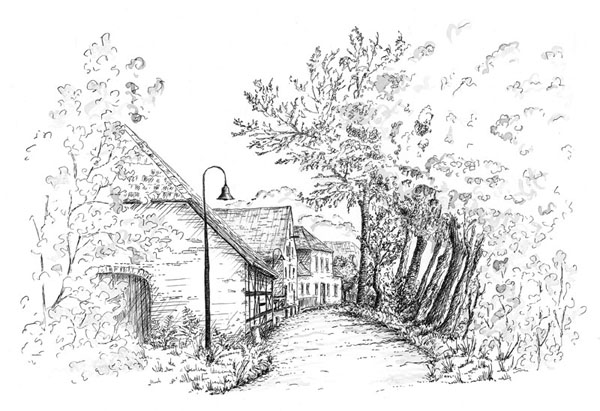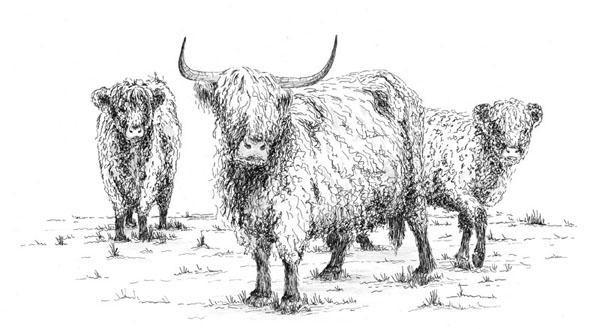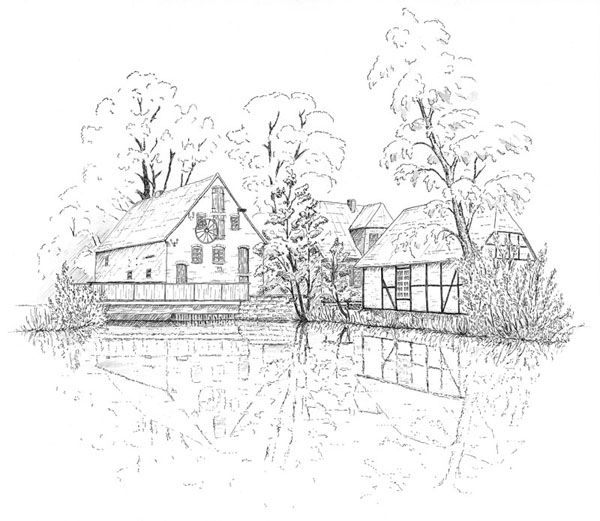
Kalendarium-Gestaltung
für ein anstehendes Kalenderprojekt bin ich auf der Suche nach Inspiration für die Gestaltung des Kalendariums. Erstmal ein paar Hinweise bzgl. des Kalenders vorweg: Es handelt sich um s/w Federzeichnungen von Gebäuden und Landschaften aus der umliegenden Gemeinde. Es soll jeweils eine Zeichnung pro Kalenderblatt gedruckt werden, das Format ist hierbei DIN-A3 quer und es wird ein Wandkalender mit einer Wire-o-Bindung. Unter dem Motiv soll natürlich ein Kalendarium abgedruckt werden und genau hierfür bräuchte ich mal eure Ideen und euer Wissen: Es soll einfarbig sein, evtl. mit Rasterung der Sonn- und Feiertage und praktisch bzw. gut lesbar sein. Die Zielgruppe des Kalenders wird vermutlich 50+ sein.
Für Ideen bzlg. der Gestaltung und der Schriftwahl wäre ich äußerst dankbar! :-)
spontan würde ich da an eine ganz pure, reduzierte Gestaltung denken: Das Kalendarium nur durch feine schwarze Linien gegliedert und eine ausdrucksstarke Schrift mit schönen Zahlen verwendet (sehr schön wären Mediävalziffern), das Ganze sehr klassisch gesetzt. Als Schrift könnte ich mir sowohl eine Serifenlose als auch eine Schrift mit Serifen vorstellen. Wichtig wäre dabei, dass die Schrift mit den Zeichnungen harmoniert und diese betont, statt ihnen die Schau zu stehlen. Könntest Du hier vielleicht mal eine der Zeichnungen einstellen? Dann könnten wir Dir Vorschläge zur Schriftenwahl machen. :-)
So, anbei sind nun drei Beispielmotive für den Kalender. Wie du schon sagtest, sollte das Kalendarium nicht von den Motiven ablenken! Ich bin gespannt auf eure Ideen :-)
Danke fürs Zeigen, die Zeichnungen kann ich mir gut als Kalender vorstellen. Welche Schriften hast Du denn bisher für die Gestaltung des Kalenders schon in Erwägung gezogen?
Ich bin noch in der frühen Anfangsphase was die Schriftwahl betrifft. Ich würde gerne zwei, drei Versionen mit unterschiedlichen Kalendarien erstellen und diese dann andrucken lassen, um damit eine praxisnahe Beurteilung an der Wand zu treffen.
Momentan spiele ich im Kalendarium mit der Helvetica Neue neue herum... gerne würde ich hierbei auf klassische Schriften zurückgreifen, die Zeitlos aber gut lesbar sind.
Da passt doch eine Antiqua.
Zu deinen Zeichnungen kann ich mir die schöne und kostenlose Vollkorn gut vorstellen.
Die würde diese ländlich-heimische Anmutung unterstützen.
Nur so, die Helvetica wäre mir zu "geht irgendwie eh mit allem".
Kann das sein, dass die Unger Fraktur kein ſ beinhaltet?
Mir wäre eine gebrochene Schrift zu dominant zu diesen fein gezeichneten Motiven. Ich würde eher die Eleganz und Zartheit der Motive in einer zurückhaltenden Typografie begleiten.
Aber sagt mal, wo ist denn eigentlich unser Threaderöffner abgeblieben? Ich hatte gehofft, dass wir schöne Kalenderentwürfe zu sehen bekommen. :-)
Mir wäre eine gebrochene Schrift zu dominant zu diesen fein gezeichneten Motiven.
Inwiefern zu dominant? Ich finde, eine feine, elegante gebrochene Schrift würde den Duktus der Zeichungen aufgreifen. Natürlich darf sie nicht allzu schwarz sein, das würde in der Tat eine zu große Dominanz der Schrift bewirken.
Du hast recht. Auf das Lang-s hatte ich gar nicht geschaut. Mir ging es prinzipiell erst einmal darum, eine Alternative zu den Antiquas vorzustellen.
… Auf das Lang-s hatte ich gar nicht geschaut. Mir ging es prinzipiell erst einmal darum, eine Alternative zu den Antiquas vorzustellen.